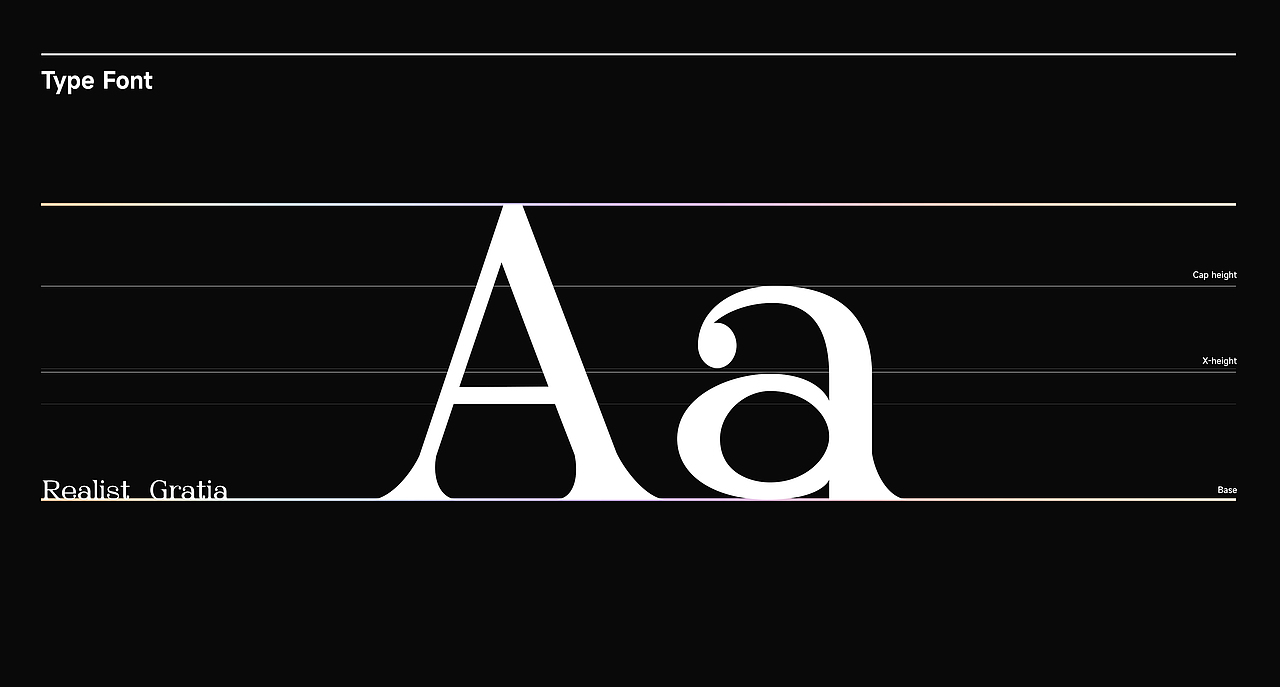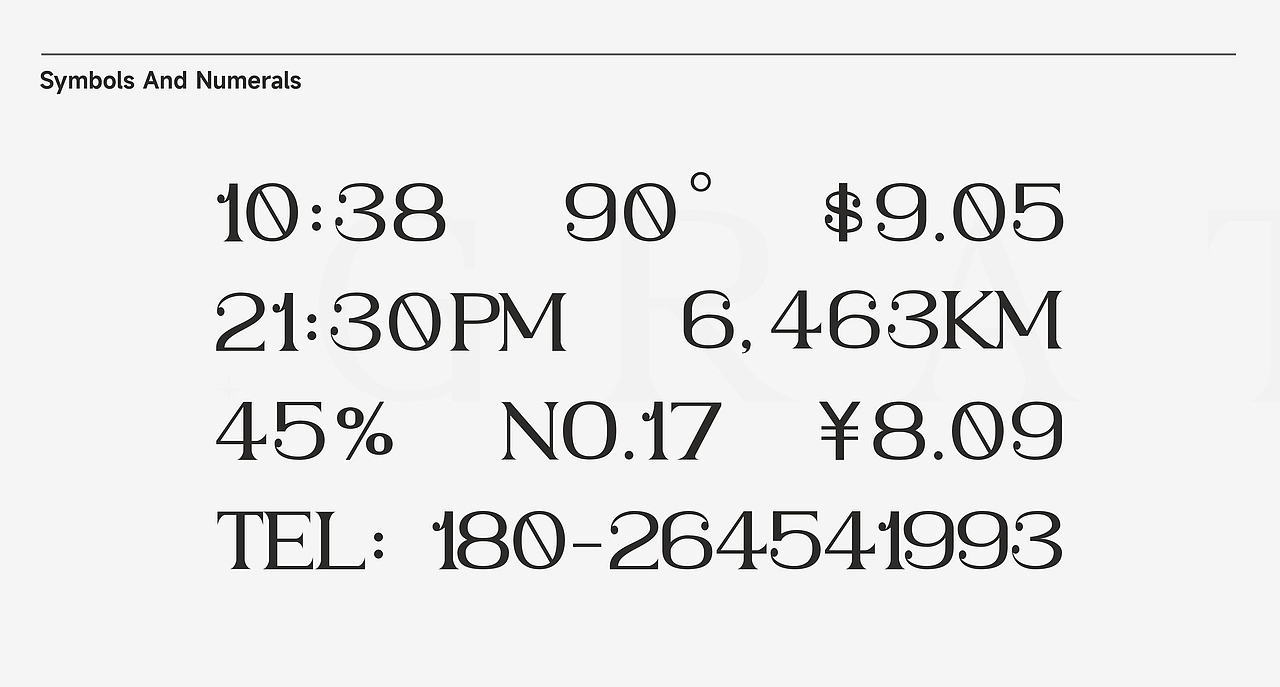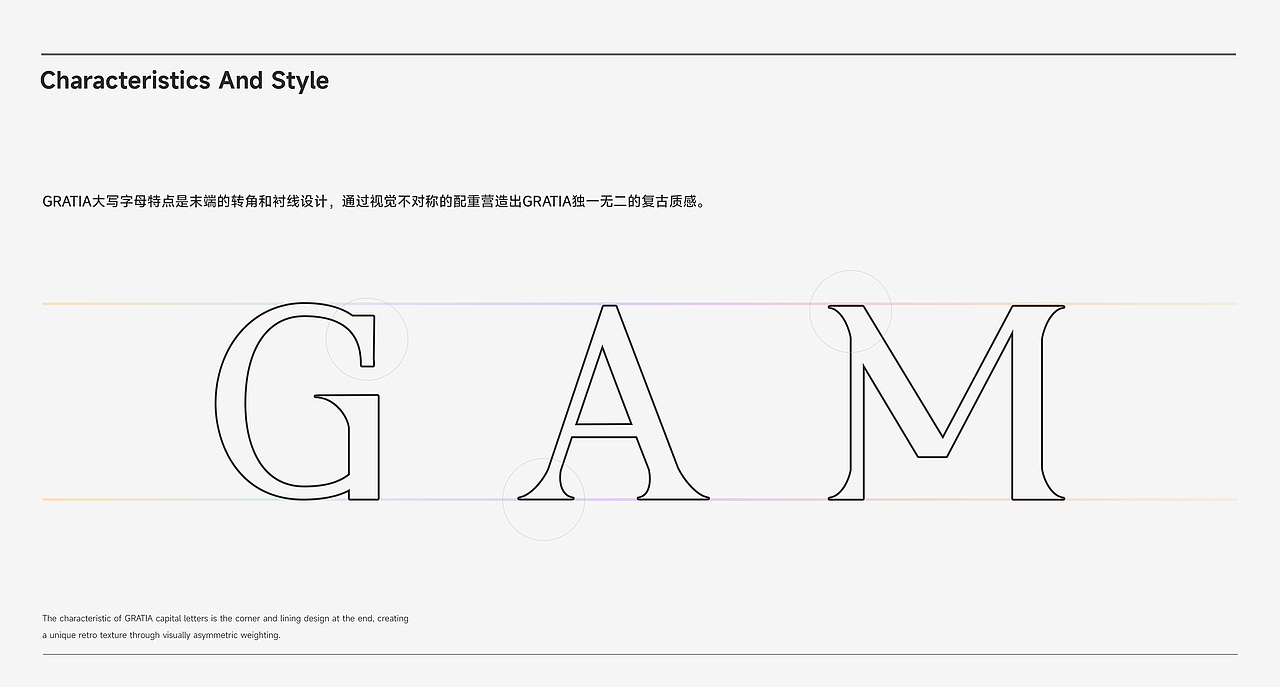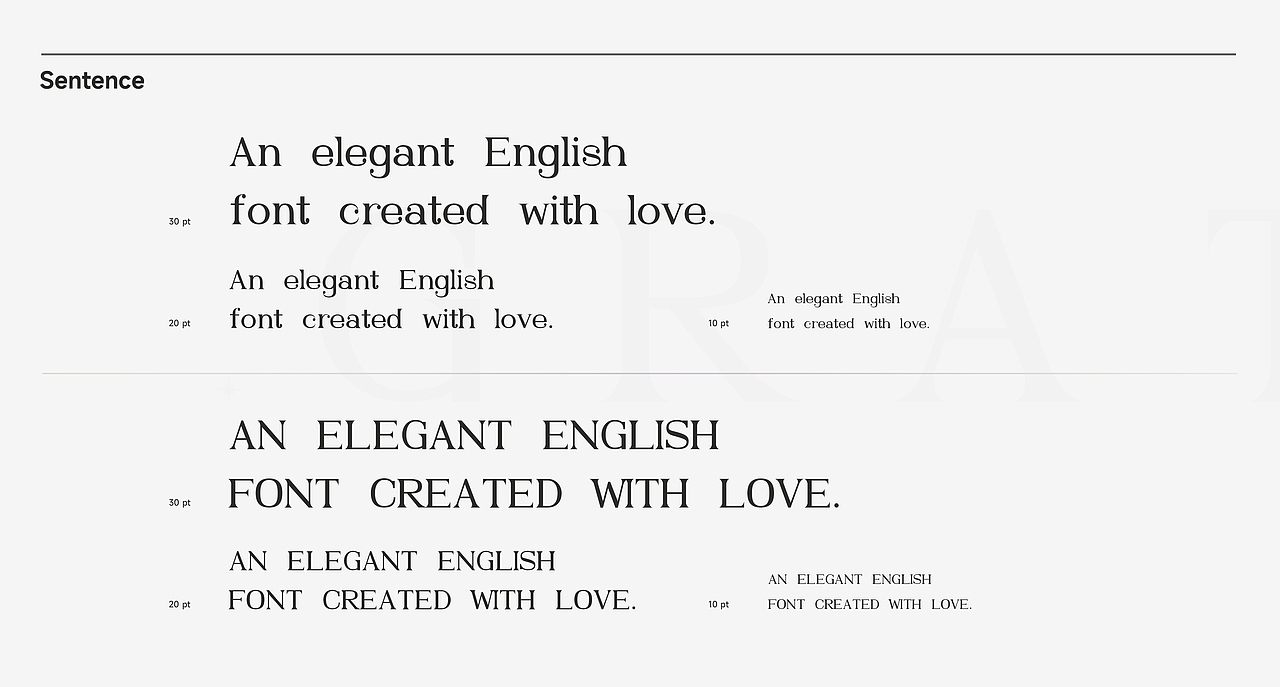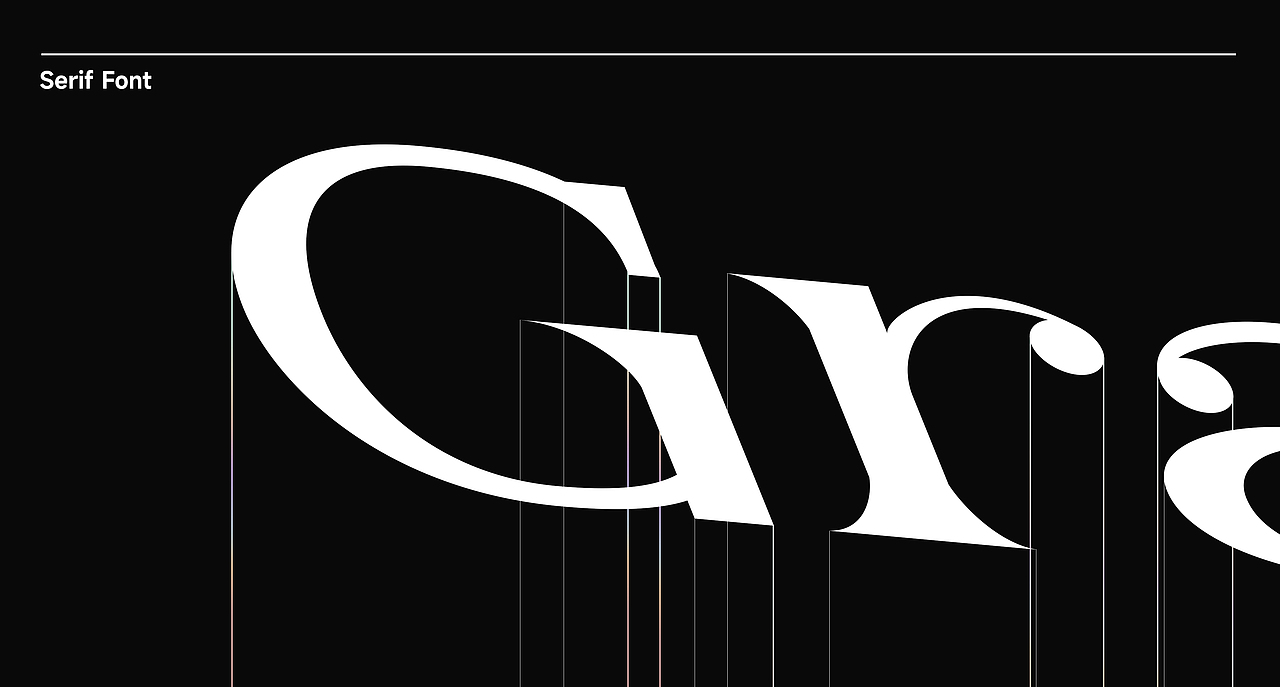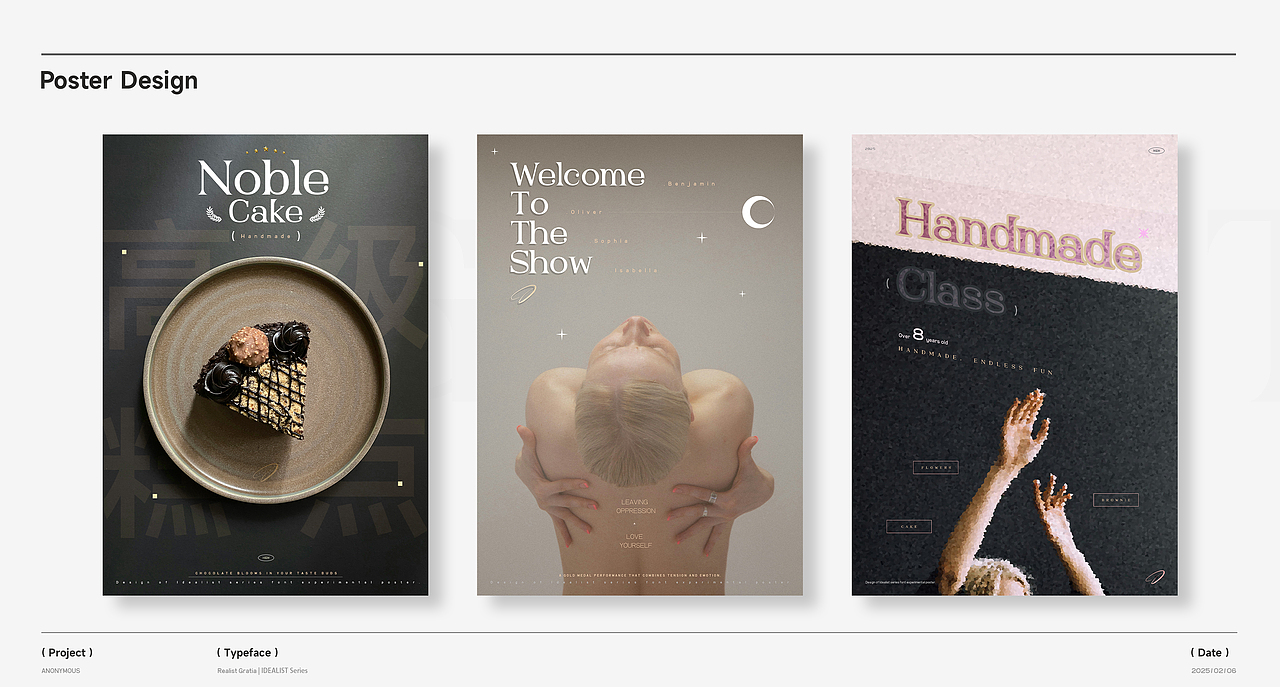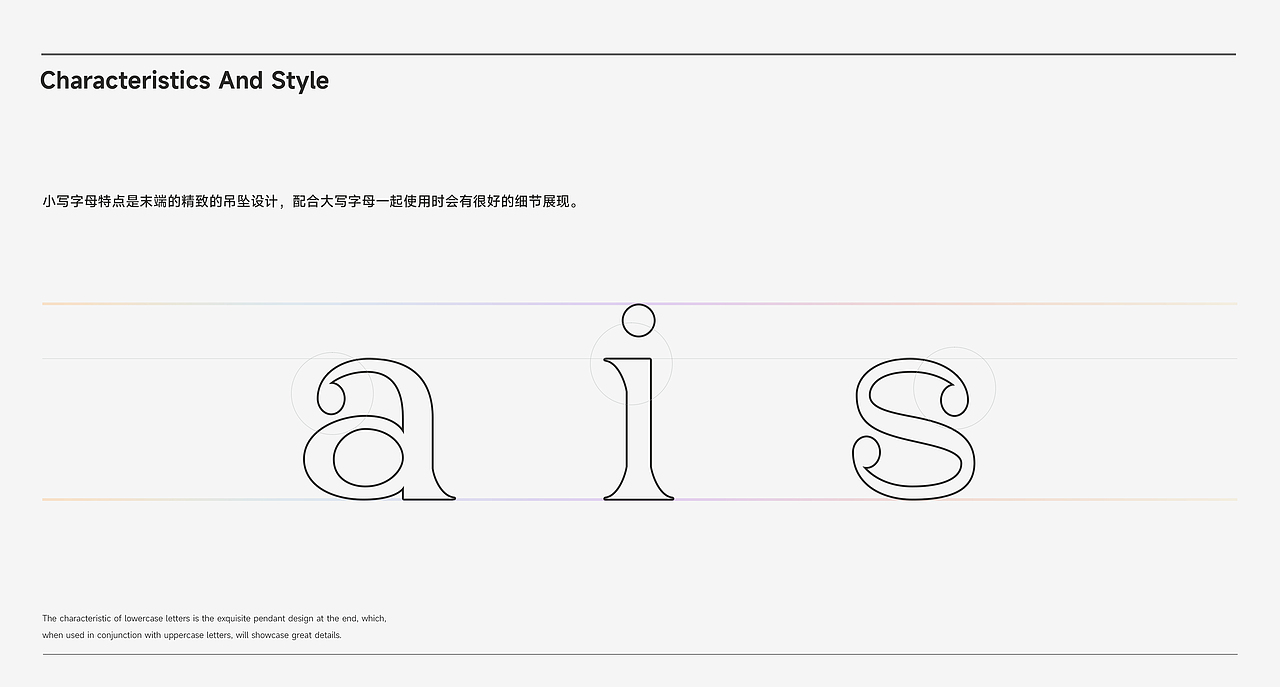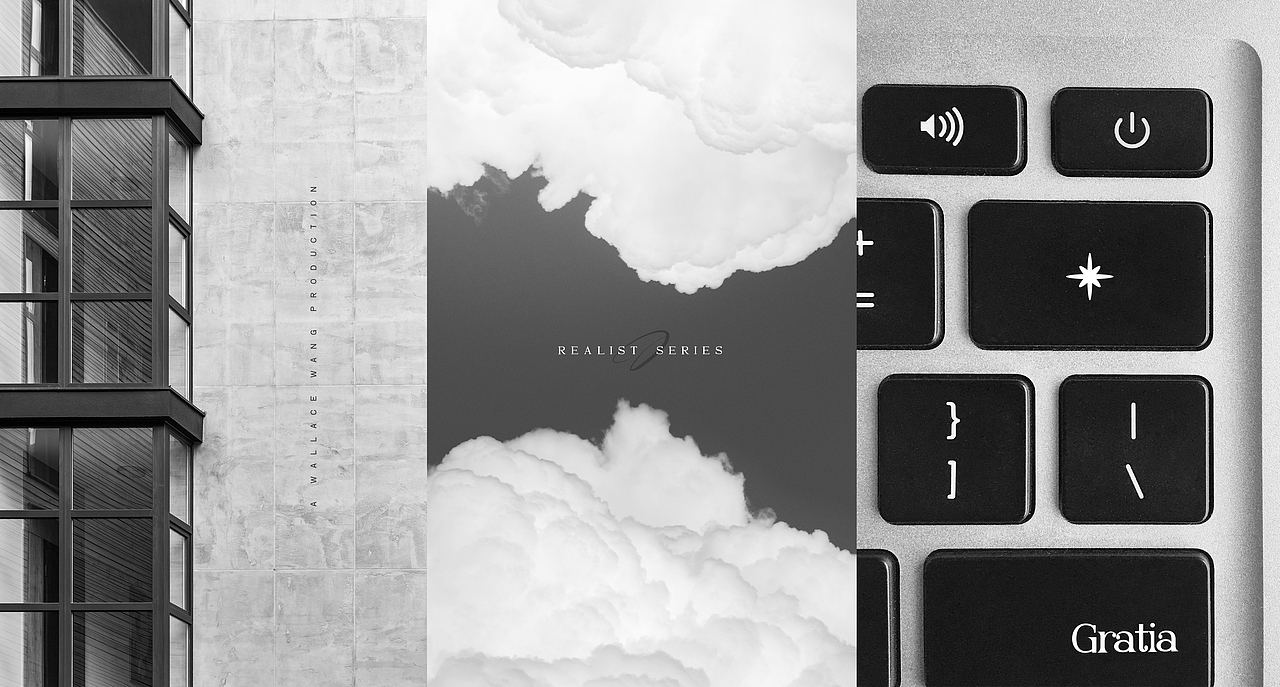
项目动因:
某天我在设计过程中,发现优雅的衬线英文字体较少,且大部分为收费的字体。刚好我之前做过的Idealist(理想主义者)系列字体是非衬线字体,于是我决定制作Realist系列(现实主义者)的衬线字体,于是诞生了Gratia。
设计思路:
陆续学习和参考了大量的衬线英文字体后,我想设计一款带有经典粗细对比,小写的时候又有精致的细节展示。于是Gratia围绕着本意(拉丁语意味-优雅),进行了创作。Gratia追求一种曲线和笔画粗细结合一种不对称的平衡美感,每个字符的设计都精心雕琢曲率,整体的呈现有一种远看优雅,细看精致的观感。
核心亮点:
复古经典的字符观感,精雕细琢的字符曲线与吊坠配重设计。更适合进行大画面标题展示的优雅呈现字体。结合了现代的流畅干净的主流观感,打造一款带有现代设计气息的优雅经典衬线英文字体。
项目成果: